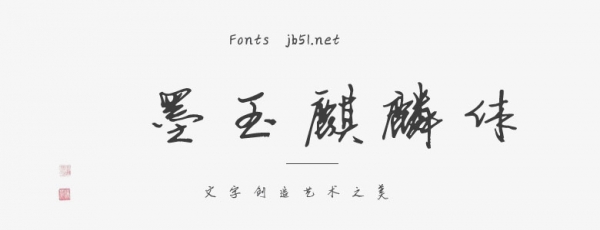
墨玉麒麟体
墨玉麒麟体,是一款承载了中华民族精神和气节的字体。字体笔势犹如山势般蜿蜒秀丽,苍劲豪纵,用笔刚柔并济,轻重有节;点画遒健英朗,逸势雄奇,宛如激荡的瀑布交响奔流,一撇一捺既有疾风劲雨的雄壮神采,也有小桥流水人家的回绕连绵。字体结构严整工稳,不失灵动隽逸,笔态恣意潇洒如行云流水,尽显端庄优雅,可以使观者联想到端庄秀美的玉石和飞檐走壁的麒麟,故得名墨玉麒麟体。